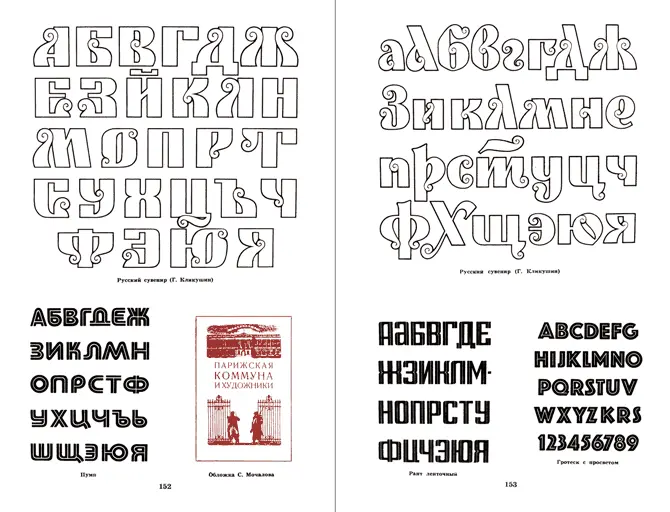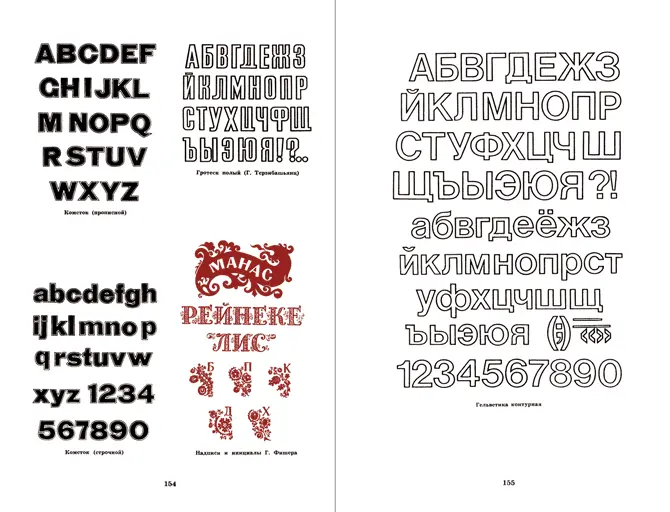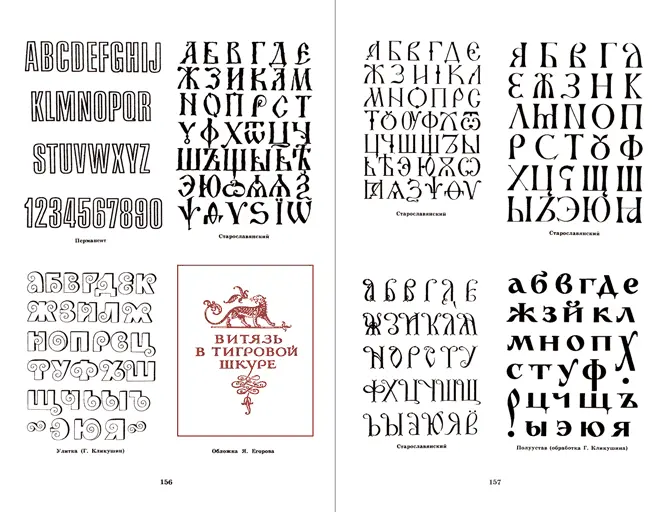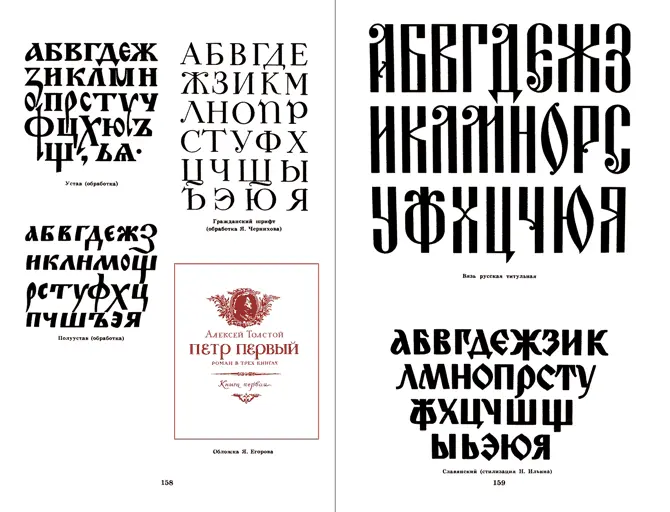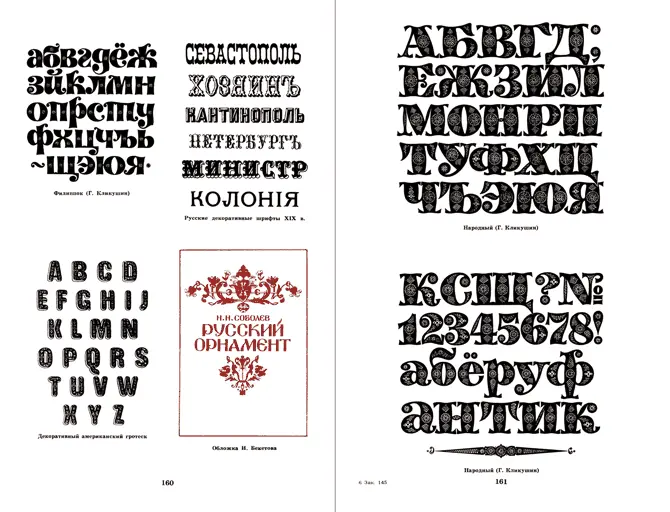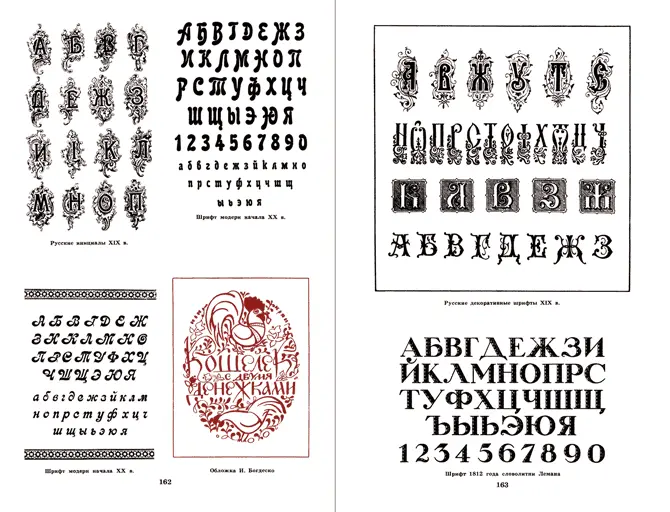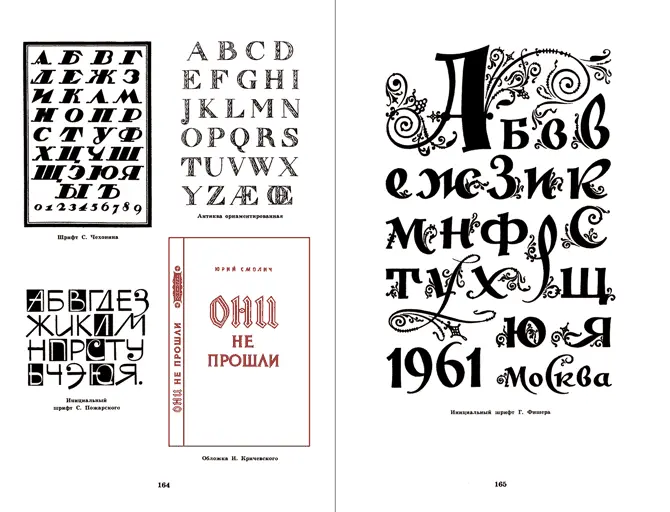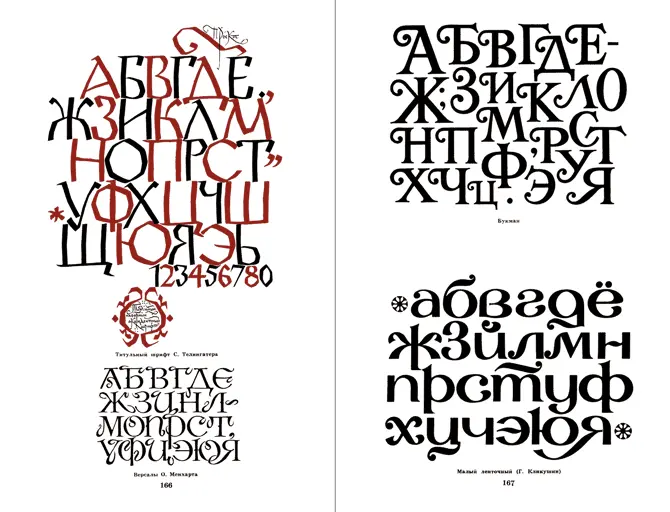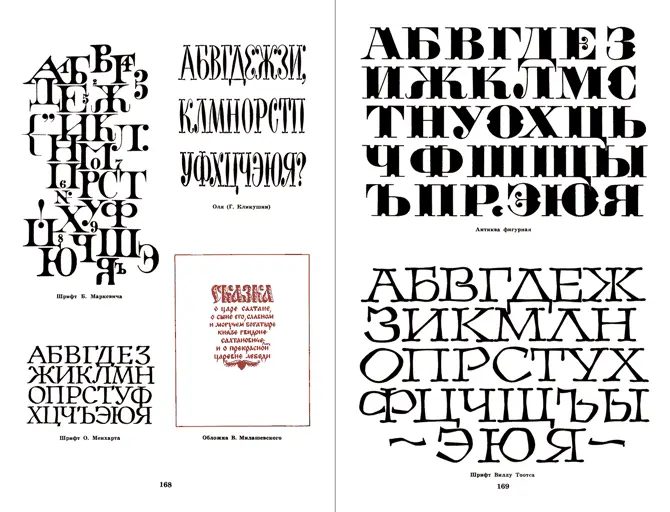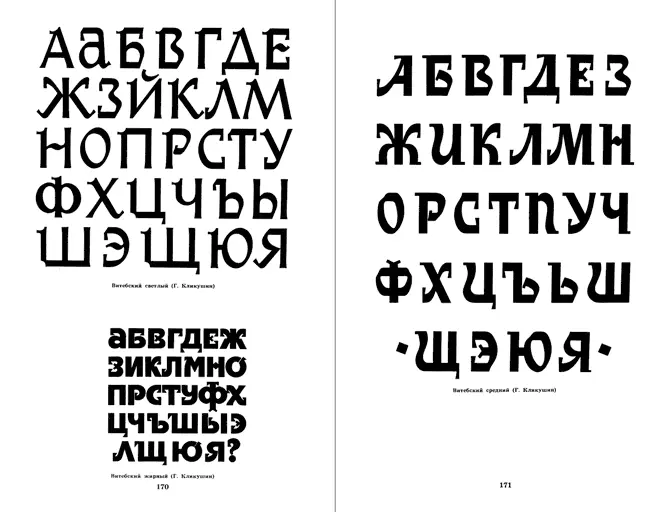
Григорий Кликушин - Шрифты для художников оформителей
В настоящем альбоме собраны книжные, плакатные и декоративные шрифты (на русской и латинской основе), которые могут быть использованы в оформительском деле: в наглядной агитации, в промышленной графике, в рекламе и в книжно-журнальном художественном оформлении.
Альбом полезен учащимся и студентам художественных учебных заведений, руководителям изостудий, учителям рисования в школах, работникам клубов и библиотек, а также всем любителям шрифтовой графики.
Русский сувенир (Г. Кликушин) * Пумп * Обложка С. Мочалова
Русский сувенир (Г. Кликушин) * Рант ленточный * Гротеск с просветом
Комсток (прописной) * Комсток (строчной) * Гротеск полый (Г. Терзибашьянц) * Надписи и инициалы Г. Фишера
Гельветика контурная
Перманент * Улитка (Г. Кликушин) * Старославянский * Обложка Я. Егорова
Старославянский * Полуустав (обработка Г. Кликушина)
Устав (обработка) * Полуустав (обработка) * Гражданский шрифт (обработка Я. Чернихова) * Обложка Я. Егорова
Вязь русская титульная * Славянский (стилизация И. Ильина)
Филиппок (Г. Кликушин) * Декоративный американский гротеск * Русские декоративные шрифты XIX в. * Обложка И. Бекетова
Народный (Г. Кликушин) * Народный (Г. Кликушин)
Русские инициалы XIX в. * Шрифт модерн начала XX в. * Обложка И. Богдеско
Русские декоративные шрифты XIX в. * Шрифт 1812 года словолитни Лемана
Шрифт С. Чехонина * Инициальный шрифт С. Пожарского * Антиква орнаментированная * Обложка И. Кричевского
Инициальный шрифт Г. Фишера
Титульный шрифт С. Телингатера * Версалы О. Менхарта
Букман * Малый ленточный (Г. Кликушин)
Шрифт Б. Маркевича * Шрифт О. Менхарта * Оля (Г. Кликушин) * Обложка В. Милашевского
Антиква фигурная * Шрифт Виллу Тоотса
Витебский светлый (Г. Кликушин) * Витебский жирный (Г. Кликушин)
Витебский средний (Г. Кликушин)
Барс (Г. Кликушин) * Гранит (П. Кузанян) * Арабский * Обложка Н. Ильина
Украинский
Дракон (китайский) * Карнас * Нимфик * Титульный лист Д. Бисти
Ринглет
Бланшард * Юбилейный * Инициалы Г. Кликушина * Суперобложка В. Фаворского
Давида
Орбита * Эксман * Велам * Обложка Г. Рифтина
Ориенте
Роберта * Гобо * Герольд (Н. Бертольд) * Итальянский (стилизация Г. Кликушина)
Чебурашка (Г. Кликушин)
Контдаун * Итальянский * Волна * Суперобложка В. Фаворского
Боттленек * Египетский декоративный
График (Э. Шнейдлер) * Пиноккио * Обложка Б. Шварца
Жетон